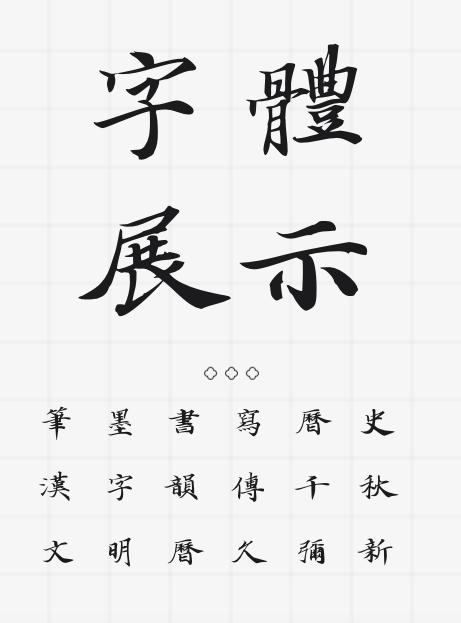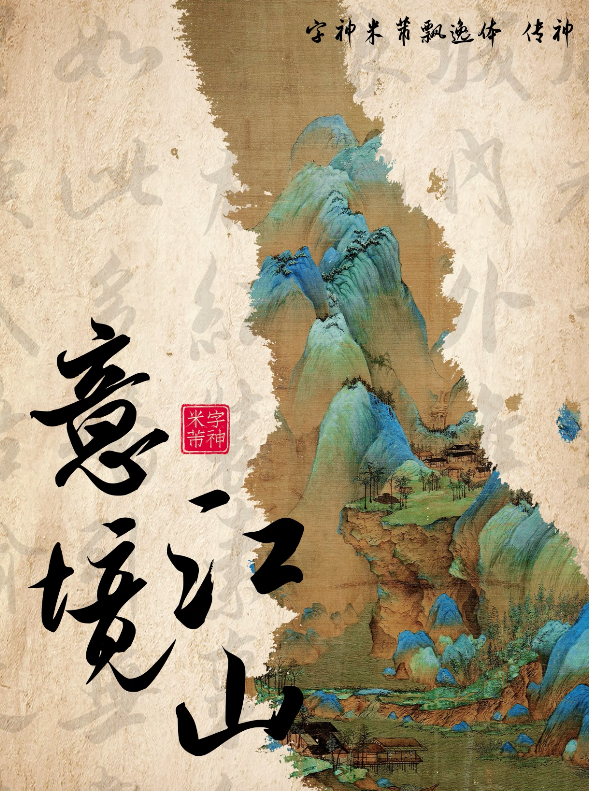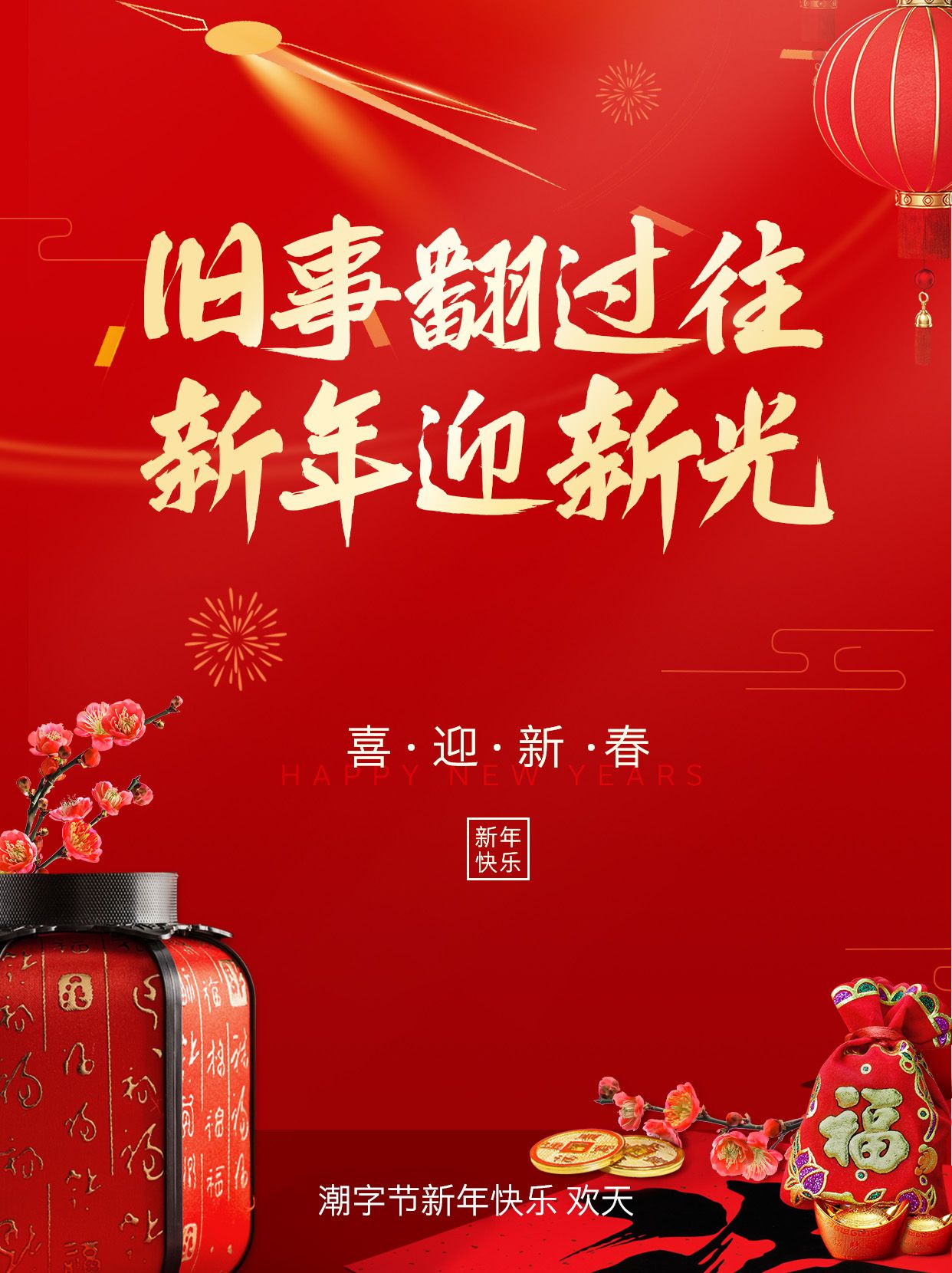
🔥武侠风来袭!这三款字体让你秒变江湖大侠✨
在武侠的世界里,文字也如同刀剑,有着自己的韵味与锋芒。今天,就让我来揭秘三款最适合武侠风格的字体,让你在文字的世界里也能成为一代大侠!💥
第一款:潮字节新年快乐🎉
这款字体结合了现代与传统元素,既有新年的喜庆,又不失武侠的豪迈。它的笔画流畅有力,如同武侠小说中的绝世剑法,每一笔都透露出不凡的气势。无论是写春联还是制作武侠小说封面,这款字体都能让你的作品充满节日的喜庆与武侠的韵味。🏮
第二款:龙书法敦煌藏经体🐉
说到武侠,怎能不提龙?这款龙书法敦煌藏经体,将龙的飘逸与敦煌文化的神秘完美融合。字体中的每一笔都仿佛蕴含着龙的力量,让人感受到一股扑面而来的武侠气息。无论是创作武侠小说标题,还是设计游戏角色名,这款字体都能让你的作品充满神秘与力量。📜
第三款:字神米芾飘逸体🌬️
米芾的书法以飘逸著称,而这款字神米芾飘逸体更是将这一特点发挥到了极致。它的笔画轻盈灵动,如同武侠小说中的轻功高手,在文字的世界里自由翱翔。使用这款字体,你的文字作品将如同武侠小说中的高手一般,充满灵动与飘逸之美。🌄
三款字体,各有千秋,都能为你的武侠风格作品增添一份独特的韵味。无论你是武侠小说作者、游戏设计师,还是热爱传统文化的你,都能在这些字体中找到属于自己的武侠梦。🌈